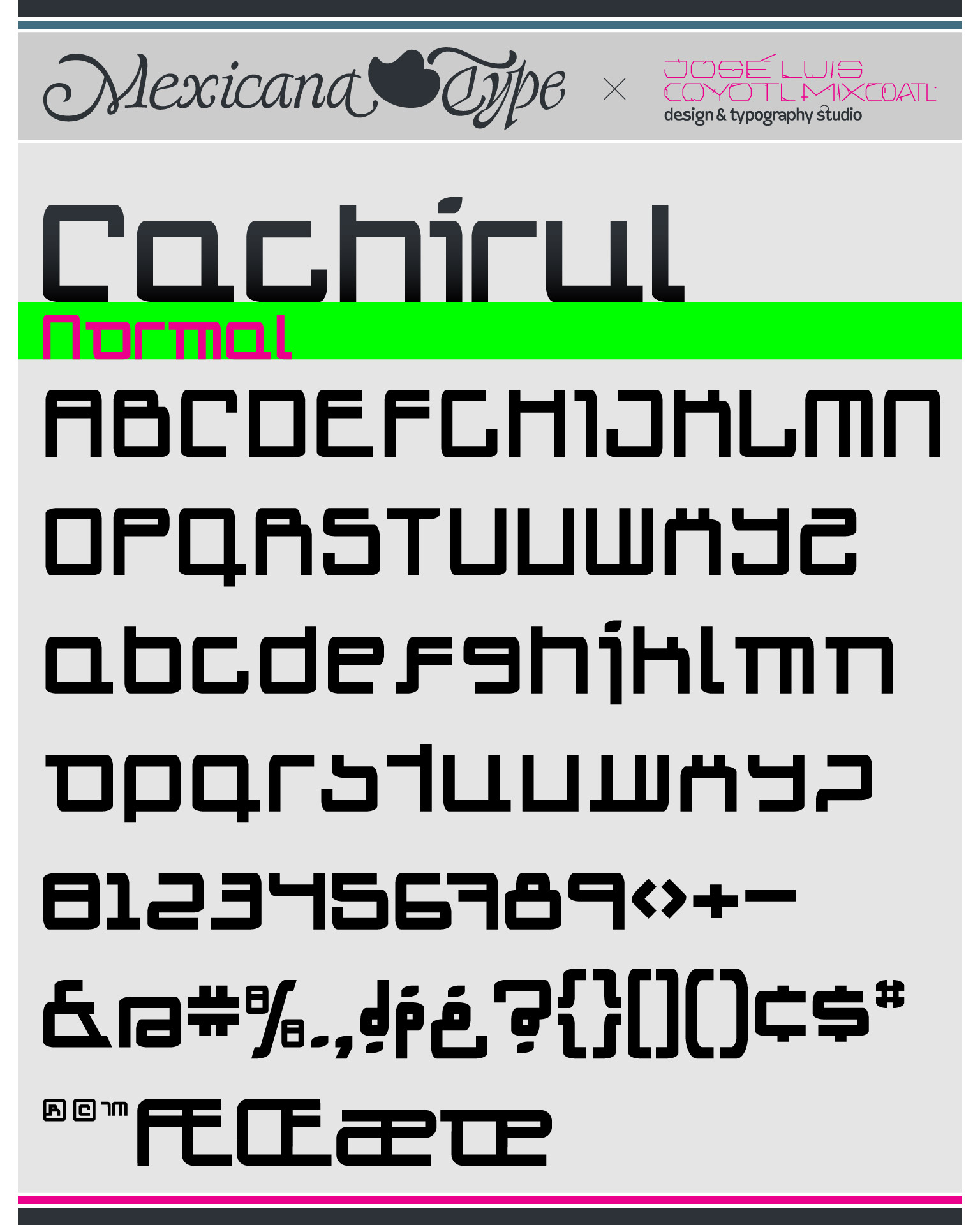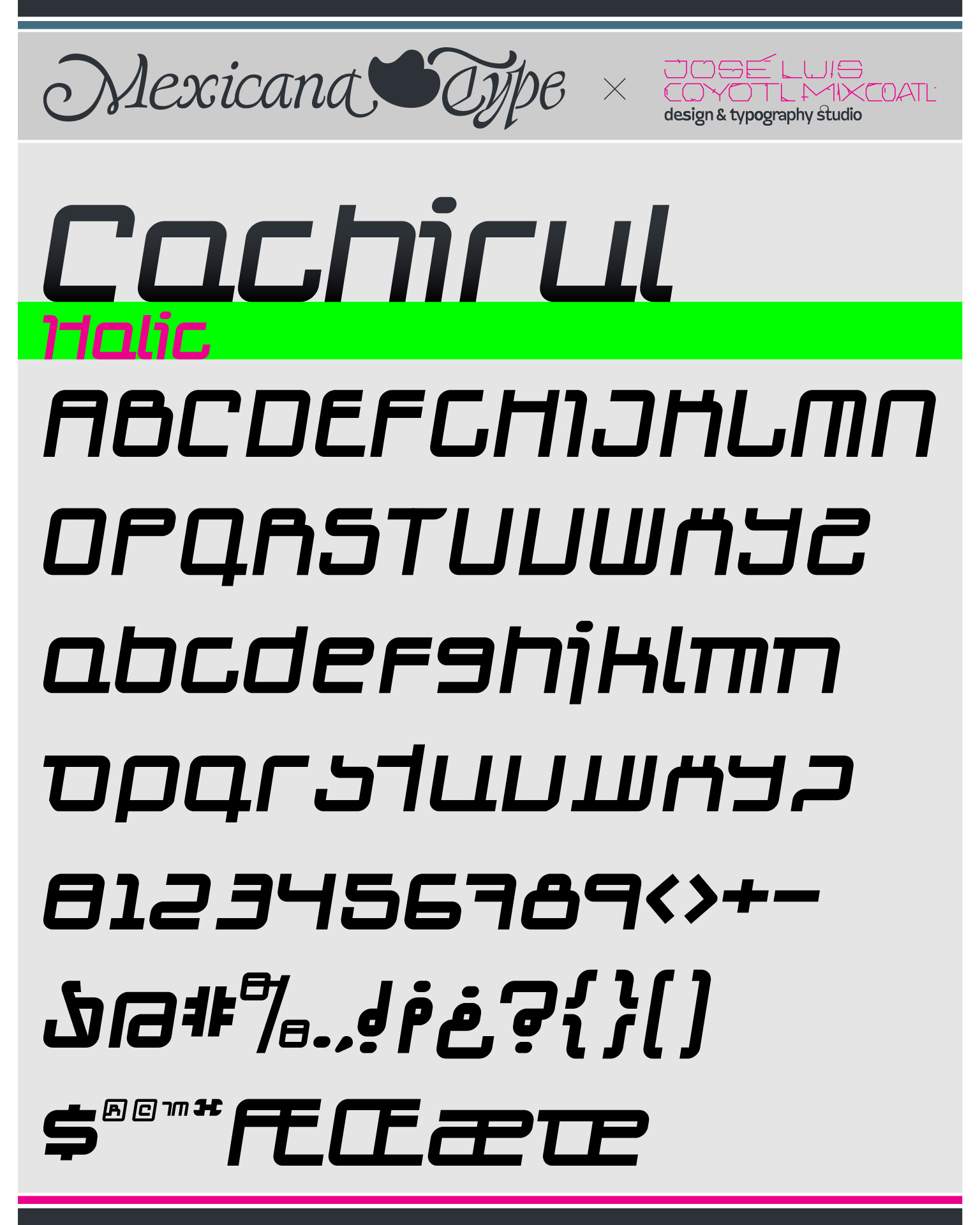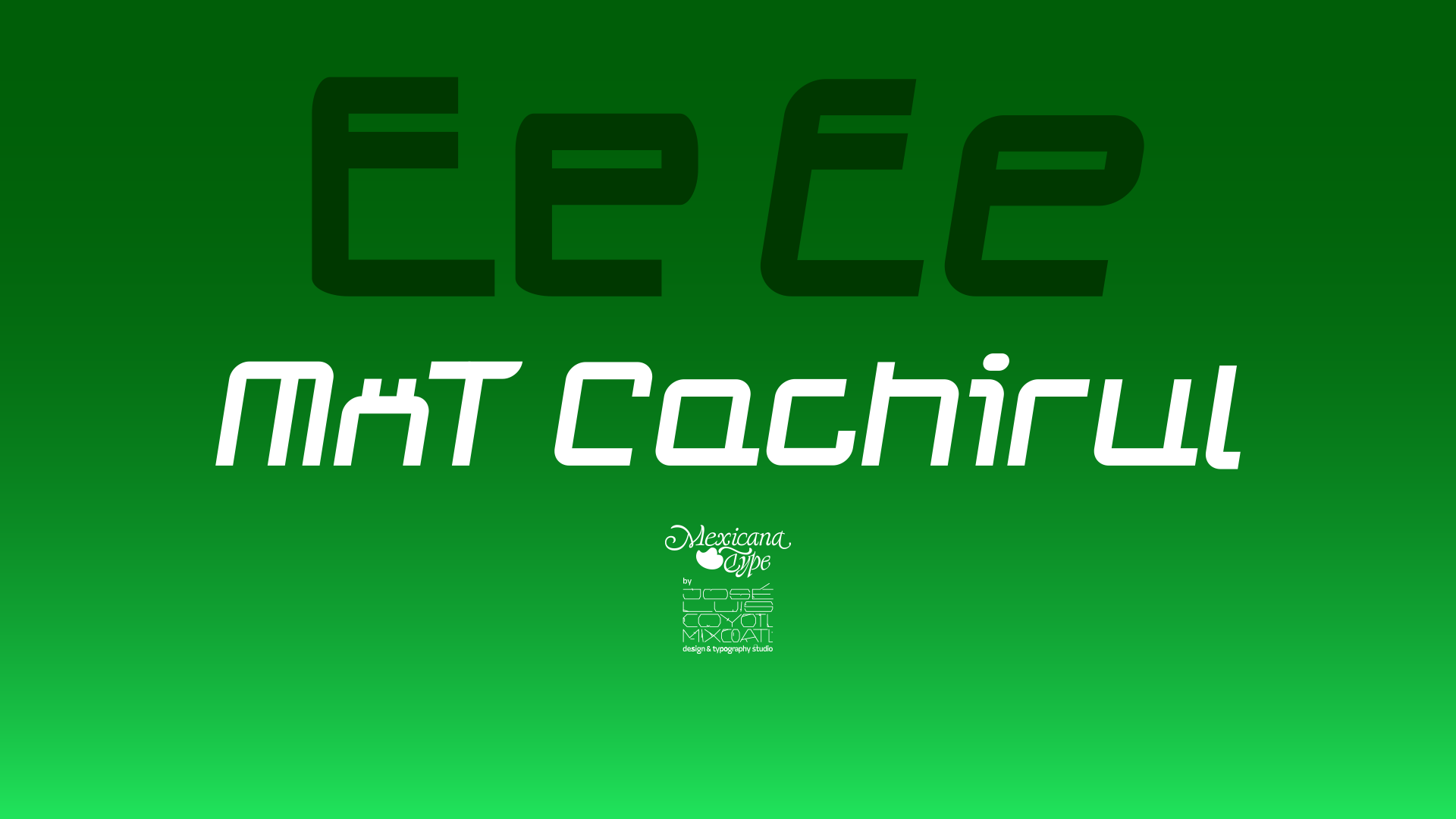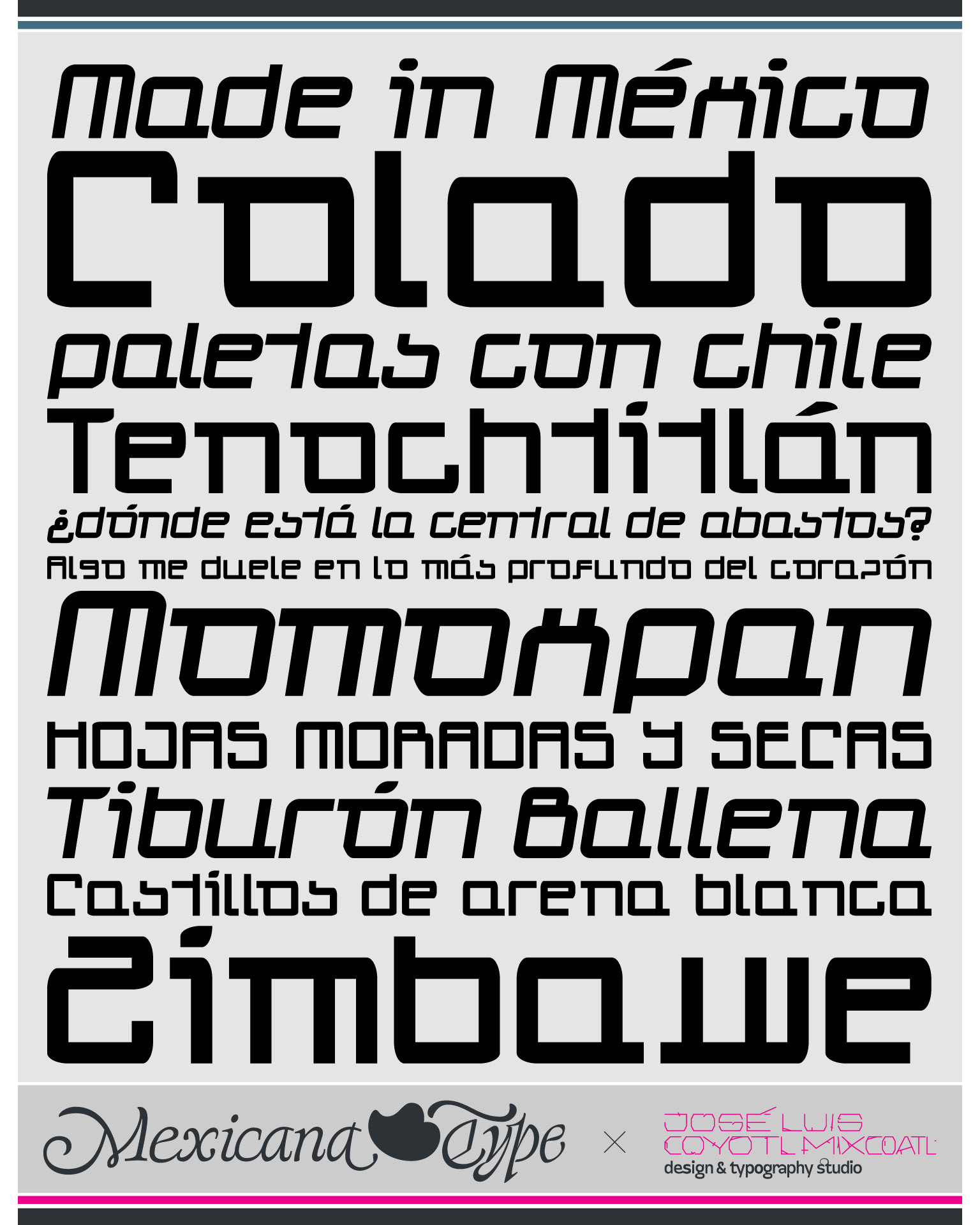
MxT Cachirul es una tipografía que experimenta con trazos geométricos y uniformes, pero con una mezcla entre asimetrías ligeras y un cuerpo esencialmente cuadrado y ángulos redondos y discontínuos, diseñada en base a las líneas que trazan una cancha deportiva de fútbol. Con dos variantes y una mancha tipográfica singular, si bien experimenta ciertos retos de lectura, es suficiente para poder tener una tipografía difícil de no poder notar.